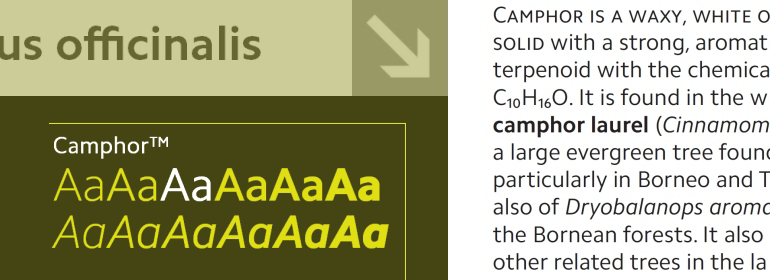
Camphor™
Camphor™,这款字体结构工整、笔画清晰,兼顾美观与易读性,适用于标题、正文、海报、包装、LOGO 等多种场景。字形优雅稳定,风格百搭耐看,适配日常排版与创意设计,让文字呈现更舒适、更具质感。Camphor™一笔一画,皆是细节,以均衡的比例、流畅的线条打造舒适视觉体验,字形端正大气,风格简约现代。无论是商业设计、品牌宣传还是日常排版,都能轻松驾驭,让文字更有格调与力量。Camphor™字体下载。
字体品牌: Monotype 设计师:Job,Nick 字体分类:衬线体、无衬线体 字体属性:外文 字符集:Unicode 发布时间: 2018